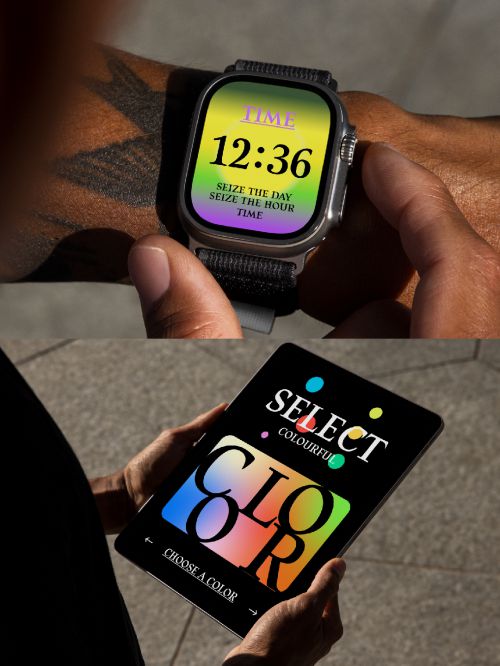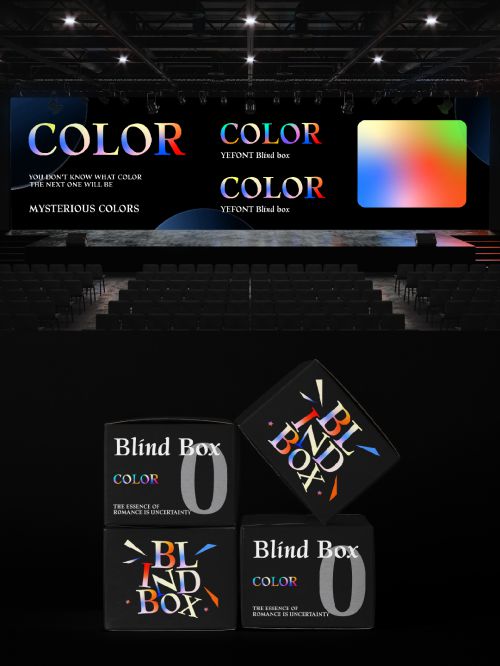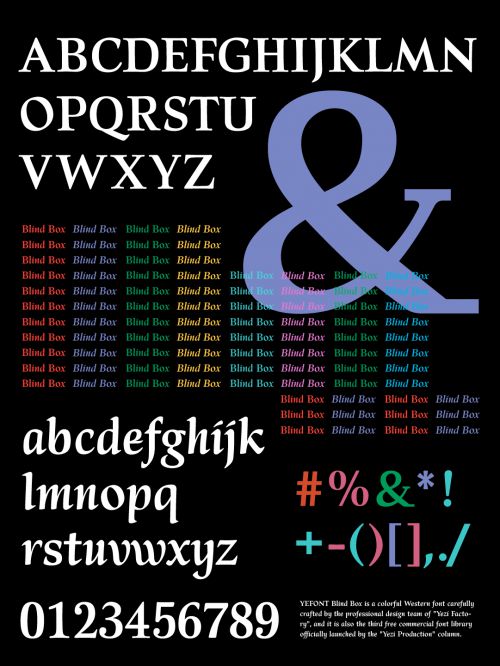
YEFONT Blind Box
YEFONT Blind Box是由也字工厂推出的英文Display字体,以突破性拼色块设计重新定义彩色字体美学。作为免费商用字体,它提供春季明亮色系、秋季柔和色系及常规单色版本,通过字母内部独立色块分割实现多元视觉表达,完美适配创意标题与品牌视觉设计。 YEFONT Blind Box的字形修长优雅,中宫宽博的结构配合居中重心,形成稳定又不失灵动的视觉平衡。笔画采用粗重均匀的方头设计,点缀斜切装饰元素与断开式笔画连接,在保持几何秩序感的同时注入活泼个性,适合打造吸睛的版面层次。 该字体包含常规字符集与多字重支持,其独特的色彩系统可满足从潮流海报到社交媒体配图的多样化需求。无论是游戏界面、时尚杂志还是节日主题设计,YEFONT Blind Box都能以鲜明的色彩碰撞与现代设计语言,为作品带来强烈的视觉冲击力和艺术感染力。